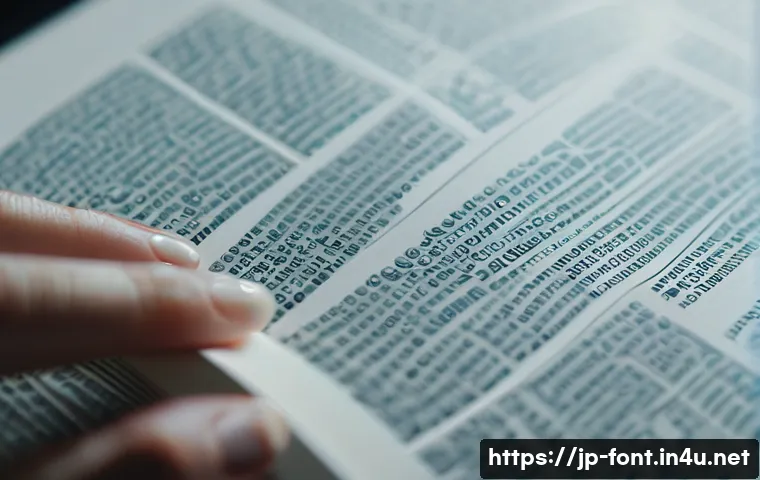
皆さん、こんにちは!日々のブログ運営やデザイン作業で、「あれ?このフォント、ウェブで表示するとイメージと違う…」なんて経験、ありませんか?私も初めてウェブサイトを作ったとき、お気に入りのフォントが画面上だと「なんか違う!」と感じて、一人で首を傾げたことがありました。実はこれ、ウェブと印刷物ではフォントの「見え方」や「使われ方」に大きな違いがあるからなんです。最近では、レスポンシブデザインが当たり前になり、どんなデバイスで見ても美しいフォント選びは本当に重要ですよね。昔は考えられなかったような表現豊かなウェブフォントも登場して、デザインの可能性はどんどん広がっています。でもその一方で、印刷物ならではの繊細な表現や、紙媒体だからこそ伝わる重厚感も捨てがたいですよね。ウェブと印刷物、それぞれの特性を理解して、最高のフォントを選ぶって、奥が深いんです!実は、この見え方の違いには、画面のピクセルと印刷のドットという根本的な表示の仕組みが関係しています。さらに、最近注目されている「可変フォント」のような新しい技術も、ウェブと印刷の境界線を曖昧にしつつあるんですよ。一体、私たちの目にはどう映り、どんな要素が影響しているのでしょうか?デザインのプロでなくても知っておきたい、ウェブと印刷フォントの秘密を、一緒にじっくり探っていきましょう!
ウェブと印刷物、そもそも「見え方」が違うのはなぜ?
ウェブサイトと印刷物で同じフォントを使っても、なぜか印象がガラリと変わってしまうこと、皆さん経験ありませんか?これ、実は画面と紙という根本的な「表示の仕組み」が違うからなんですよね。私も初めてウェブサイトを立ち上げた時、お気に入りの明朝体が思ったより細く見えたり、ゴシック体が野暮ったく感じたりして、すごく戸惑いました。画面は光の三原色(RGB)で色を表現し、ピクセルという小さな点々で文字を構成しています。だから、特に細い線や複雑なディテールを持つフォントだと、ピクセルが粗いとどうしてもギザギザしたり、滲んで見えたりしちゃうんです。特にRetinaディスプレイのような高解像度ならまだしも、そうでない環境だと顕著に差が出ますよね。一方、印刷物はインクの四原色(CMYK)で色を混ぜて表現し、ドット(点)の密度で細かさを決めています。紙にインクが乗ることで、文字そのものに物理的な厚みや重みが加わる。この「物理的な存在感」が、ウェブとは全く違う読み心地を生み出すんです。だから、同じ「フォント」という名前でも、ウェブと印刷ではまるで別物、くらいの心構えで選ぶのが私のこだわりです。
ピクセルとドット、表示の仕組みが根本的に違う
私たちは普段、あまり意識することはありませんが、パソコンやスマートフォンの画面は「ピクセル」という小さな光の点で画像や文字を表示しています。一方、雑誌や書籍、ポスターなどの印刷物は「ドット」というインクの点で表現されます。この違いが、フォントの見え方を大きく左右するんですよ。例えば、明朝体の「はね」や「とめ」のような繊細な部分は、ピクセルの粗さによっては正確に再現されず、カクカクして見えたり、最悪の場合は潰れて読みにくくなってしまうこともあります。でも、印刷物なら高精細なドットで表現されるため、細部までくっきりと美しく再現されるんです。私がデザインの仕事で特に気をつけているのは、ウェブで使うフォントは「ピクセルパーフェクト」を意識して、いかに画面上で美しく見えるかを追求すること。反対に印刷物では、紙の質感を活かしつつ、インクが滲むことを考慮したフォント選びを心がけています。
ブラウザやOSによる表示の違いを理解する
ウェブフォント選びのもう一つの落とし穴は、ブラウザやOSによってフォントの見え方が微妙に異なる点です。同じフォントでも、ChromeとSafari、WindowsとmacOSではレンダリング(描画)エンジンが違うため、文字の太さや間隔、アンチエイリアス(文字の縁を滑らかにする処理)のかかり方が変わってきます。これがまたデザイナー泣かせなんですよね!私も以前、とあるプロジェクトでこだわって選んだフォントが、特定のブラウザだと少し細く見えてしまい、クライアントから「イメージと違う」と指摘された苦い経験があります。その経験以来、フォントを決定する際は必ず複数のブラウザやOSでテストするようにしています。特に企業のコーポレートサイトなど、多くのユーザーが利用する可能性のあるサイトでは、どんな環境でも一定の品質を保つことが信頼感に繋がると痛感しています。
「ウェブフォント」の進化がデザインにもたらしたもの
昔のウェブサイトでは、ユーザーのパソコンにインストールされている「システムフォント」しか使えませんでした。だから、デザインの自由度が本当に低くて、どのサイトも似たような見た目になりがちでしたよね。それが「ウェブフォント」の登場で、ガラッと世界が変わったんです!私も初めてGoogle Fontsを使ったときは、あまりの種類の多さと手軽さに感動したのを覚えています。ウェブフォントは、サーバーからフォントデータを読み込むことで、ユーザーの環境に依存せず、デザイナーが意図した通りのフォントを表示できる画期的な技術です。これにより、ウェブサイトのデザイン表現の幅が飛躍的に広がり、ブランドイメージに合ったオリジナリティあふれるサイト制作が可能になりました。まるで紙媒体のように、ウェブでもフォントの個性を存分に活かせるようになったんです。今では無料のサービスも充実していて、私もよく活用させてもらっています。
デザインの表現力を格段に引き上げるウェブフォント
ウェブフォントの最大の魅力は、やはりデザインの表現力を格段に引き上げてくれる点だと感じています。システムフォントに縛られていた時代には考えられなかったような、個性的で美しい書体を使えるようになったことで、ウェブサイト全体の世界観をより豊かに、より深く伝えられるようになりました。例えば、カフェのサイトであれば手書き風の温かみのあるフォントを、テクノロジー系の企業サイトであればシャープでモダンなフォントを、といった具合に、コンテンツのメッセージやブランドイメージに合わせてフォントを自由に選べるのは本当に素晴らしいことです。私自身、あるブランドのウェブサイトを制作する際に、ウェブフォントを導入したことで、テキスト情報だけでなく、フォントそのものが持つ「雰囲気」によってブランドの価値を格段に高められたと実感しています。フォントが持つ印象は、写真やイラストと同じくらい、いやそれ以上に重要だとさえ思っています。
パフォーマンスと読み込み速度、賢く選ぶには
ウェブフォントは非常に便利ですが、同時に注意すべき点もあります。それは「パフォーマンス」です。フォントデータをサーバーから読み込むため、フォントの種類や量によってはウェブサイトの読み込み速度が遅くなってしまうことがあります。これ、ユーザー体験を損なうだけでなく、SEOの評価にも響いてくるので、特に気をつけたいところです。私も以前、たくさんのウェブフォントを使いすぎて、サイトの表示がもっさりしてしまった経験があり、それからはフォントの数を厳選し、必要なウェイト(太さ)だけを読み込むように工夫しています。例えば、本文はシステムフォントに近いウェブフォントを使って負荷を減らし、見出しや重要なキャッチコピーにのみ、個性の強いウェブフォントを使用するなど、メリハリをつけるのがおすすめです。読み込み速度とデザイン性のバランスをいかに取るか、これがウェブフォントを賢く活用するカギだと感じています。
印刷物でこそ活きる!紙媒体ならではのフォント選びの醍醐味
ウェブフォントが便利だからといって、印刷物のフォント選びがおろそかになっていいわけではありません。むしろ、印刷物だからこそ輝くフォントの魅力って、たくさんあるんですよ!紙に印刷された文字は、デジタルデバイスの画面とは一線を画す「重厚感」や「品格」をまといます。手に取った時の紙の質感、インクの匂い、そして文字が紙の上に確かに存在するという感覚は、デジタルでは味わえないものです。特に、高級感を出したいカタログや、読み応えのある書籍、歴史を感じさせるパンフレットなどでは、印刷物ならではのフォント選びがデザインの成否を分けると言っても過言ではありません。私も自分のポートフォリオを紙媒体で制作した際、ウェブでは使わないような、線の抑揚が美しい明朝体を選んだのですが、実際に印刷されたものを見た時の感動は忘れられません。やはり、紙とインクが織りなすフォントの表情は格別だな、と改めて感じました。
紙の質感とインクが織りなすフォントの表情
印刷物におけるフォント選びは、紙の種類やインクの色との相性を考えるのが本当に楽しいんです。例えば、ざらっとした手触りの上質紙に太めのゴシック体を印刷すると、インクが紙に少し滲んで、独特の温かみのある印象になります。一方、ツルツルとした光沢のあるアート紙に細めの明朝体を印刷すると、文字のエッジがシャープに際立ち、洗練された雰囲気を演出できます。この紙とインク、そしてフォントの組み合わせによって無限の表情が生まれるのが、印刷デザインの醍醐味だと私は思っています。ウェブでは画面のバックライトが均一なので、そこまで細かく背景と文字の質感の相性を考えることは少ないですが、印刷物では光の当たり方や紙の影までがフォントの印象に影響を与えるんですよ。だからこそ、サンプル印刷を重ねて、理想の仕上がりを追求する時間は、デザイナーにとって至福のひとときなんです。
可読性と美しさを両立させる伝統的な書体
印刷物では、長年の歴史の中で培われてきた「伝統的な書体」が持つ可読性と美しさが最大限に活かされます。特に書籍の本文など、長文を読ませる場面では、読み疲れしにくいように設計された明朝体やセリフ体が非常に効果的です。これらの書体は、文字一つ一つのエレメントが非常に緻密にデザインされており、紙の上で美しく、そして快適に読めるように工夫されています。私自身、歴史書や文学作品を読むのが好きなのですが、やはり文字が美しく、目が滑らかに動くようなレイアウトとフォントで組まれていると、物語の世界に没入しやすくなります。逆に、ウェブでは視認性を重視してゴシック体が使われることが多いですが、印刷物では明朝体の持つ繊細な美しさが、より深い読書体験へと誘ってくれるんです。伝統的な書体の持つ力を再認識し、現代のデザインにどう活かすか、常に探求しています。
これで失敗しない!ウェブと印刷、それぞれのフォント選びのコツ
ここまでウェブと印刷物でフォントの見え方が違う理由や、それぞれの魅力についてお話してきましたが、じゃあ具体的にどうやってフォントを選べばいいの?と疑問に思いますよね。私も昔はたくさん失敗して、「あちゃー!」となった経験が山ほどあります。でも、いくつかのコツさえ押さえておけば、もうフォント選びで頭を抱えることはありません。大切なのは、まず「誰に何を伝えたいのか」という目的を明確にすること。そして、その目的に合わせてウェブと印刷、それぞれの特性を理解し、フォントが持つ力を最大限に引き出すことです。ウェブでは「読みやすさ」と「表示速度」、印刷では「可読性」と「質感」を特に意識するといいですよ。また、最近ではフリーで使える高品質なフォントもたくさんありますから、色々と試して自分のお気に入りを見つけるのも楽しいです。
ウェブコンテンツに最適な「視認性」重視のフォント
ウェブサイトのフォント選びで最も重視すべきは、やはり「視認性」と「読みやすさ」です。画面上で情報を素早く正確に伝えるためには、一目見て内容が頭に入ってくるようなフォントを選ぶ必要があります。私がウェブサイトをデザインする際によく使うのは、やはり「ゴシック体」が多いですね。特に、日本語フォントであれば「Noto Sans JP」や「Yu Gothic」などが定番で、シンプルで癖がなく、様々なデバイスやブラウザで安定して表示されるので安心感があります。最近は「M PLUS Rounded 1c」のような丸ゴシック体も、親しみやすい印象を与えたいサイトでよく使います。大切なのは、文字が小さくなっても潰れず、遠目からでも識別しやすいこと。そして、長文でも目が疲れにくいように、適度な文字間隔や行間を設定することも忘れてはいけません。フォント選びは、ユーザーに寄り添うデザインの第一歩だと私は考えています。
質問: 最近話題の「可変フォント」って何ですか?ウェブデザインにどう役立つのでしょうか?
回答: 「可変フォント」、私も初めて聞いたときは「何それ、すごい!」って感動しました。最近のウェブデザイン界隈では、本当にホットな話題ですよね!これまでのフォントの概念をガラッと変える、まさに「次世代フォント」なんです。簡単に言うと、可変フォントは「一つのフォントファイルの中に、太さや幅、傾きなど、あらゆるスタイル情報を可変データとして持っている」フォントのことなんです。 これまでのフォントって、「Light」「Regular」「Bold」みたいに、太さごとに別々のファイルを用意して読み込む必要がありましたよね?私も色々な太さを使いたい時に、ファイルの数が増えてサイトが重くなるのが悩みだったんですが、可変フォントならその心配がほとんどないんですよ。たった一つのファイルで、細いものから極太まで、間のウェイトも数値で自由に、滑らかに調整できちゃうんです! まるで、フォントに無限のバリエーションが詰まっているような感覚です。ウェブデザインにおけるメリットは、本当に計り知れません。まず、何と言っても「ファイルサイズの削減と読み込み速度の向上」です。複数のフォントファイルを読み込む必要がなくなるので、サイト全体のデータ量を大幅に減らせる可能性があります。 これはSEOにとっても、ユーザー体験にとっても、本当に嬉しいポイントですよね。私もこのおかげで、サイトの表示がサクサクになって、読者さんの滞在時間が延びたように感じています!そして、デザイナーにとっては「デザインの自由度が格段に上がる」ことが一番の魅力ではないでしょうか。従来のフォントでは「Regularだとちょっと弱いけど、Boldだと強すぎる…」というジレンマに陥りがちでしたが、可変フォントならその中間を自由に設定できます。 レスポンシブデザインで狭いスペースにテキストを収めたい時も、文字の幅を微妙に調整して「収まりよく」見せるといった、これまで不可能だったような繊細なタイポグラフィの調整が可能になるんです。 CSSのプロパティを使えば、インタラクティブに文字の表情を変えることもできるので、クリエイティブな表現の幅がグッと広がりますよ。Adobe FontsやGoogle Fontsでも対応が進んでいるので、皆さんもぜひ試してみてほしいですね。 私もこの技術のおかげで、ウェブと印刷物、両方のデザインでフォント選びがもっと楽しく、そして効率的になりました!まさに、未来を感じるフォントの進化だと思っています。